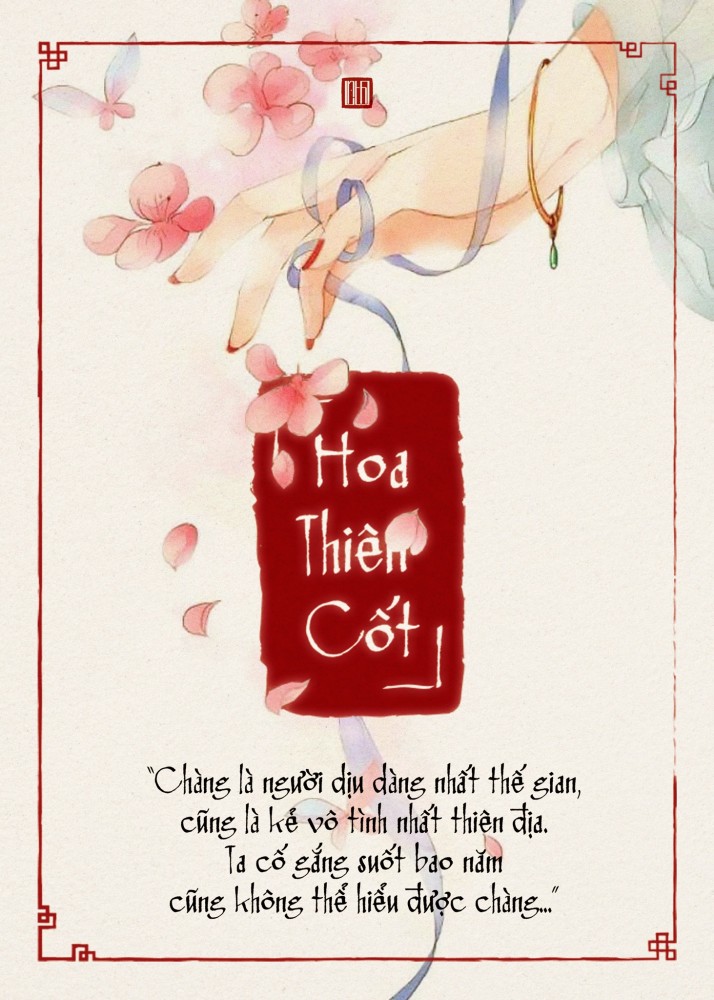
Khám phá sự độc đáo của Font việt hóa LNTH Dieter Steffmann trong thiết kế
Trong thế giới thiết kế đồ họa, việc lựa chọn Font Chữ phù hợp đóng vai trò then chốt trong việc truyền tải thông điệp và tạo ấn tượng thị giác. Gần đây, cộng đồng thiết kế Việt Nam đang dành sự quan tâm đặc biệt cho một tác phẩm nghệ thuật chữ cái: Font việt hóa LNTH Dieter Steffmann. Đây không chỉ là một bộ font thông thường, mà còn là sự kết hợp tinh tế giữa nét cổ điển Châu Âu và khả năng ứng dụng linh hoạt trong ngôn ngữ Tiếng Việt. Bộ font này, vốn được phục chế từ các mẫu chữ lịch sử bởi Dieter Steffmann, đã được nhóm LNTH việt hóa một cách tỉ mỉ, mở ra cánh cửa sáng tạo mới cho các dự án đòi hỏi sự trang trọng, cổ kính và độc đáo. Chúng ta sẽ cùng đi sâu tìm hiểu về lịch sử, đặc điểm và cách tối ưu hóa việc sử dụng bộ font tuyệt vời này.
Font việt hóa LNTH Dieter Steffmann: Khi cổ điển gặp hiện đại
Bộ font này là một ví dụ điển hình về sự giao thoa giữa nghệ thuật phục chế font chữ và công nghệ việt hóa hiện đại. Dieter Steffmann, một nhà phục chế font nổi tiếng người Đức, đã dành nhiều năm để số hóa và tái tạo lại hàng trăm mẫu chữ cổ điển từ các bản in lịch sử. Các tác phẩm của ông thường mang đậm phong cách Calligraphy (thư pháp) hoặc Blackletter (chữ Gothic), tạo nên vẻ đẹp trang nghiêm, hoài cổ mà hiếm có phông chữ hiện đại nào có thể sánh được. Khi bộ font gốc được nhóm LNTH (có thể là một nhóm Việt hóa font uy tín) tiếp nhận, thách thức lớn nhất là làm thế nào để giữ nguyên tinh thần cổ điển đó đồng thời bổ sung đầy đủ các ký tự tiếng Việt (dấu thanh, chữ cái có dấu mũ, v.v.).
Dieter Steffmann và di sản phục chế font
Dieter Steffmann không chỉ là người số hóa; ông là người bảo tồn di sản chữ viết. Công việc của ông giúp cho các nhà thiết kế ngày nay có thể tiếp cận những kiểu chữ đã từng thịnh hành từ thế kỷ 18, 19. Các font chữ của ông thường được chia sẻ miễn phí cho mục đích cá nhân, điều này đã giúp các tác phẩm như Font việt hóa LNTH Dieter Steffmann trở nên phổ biến nhanh chóng. Chất lượng phục chế cao, đường nét sắc sảo, và cấu trúc chữ cân đối là những yếu tố khiến các font của Steffmann được giới chuyên môn đánh giá rất cao. Điều này đặt nền móng vững chắc cho quá trình việt hóa sau này.
Đặc điểm nổi bật của phông chữ LNTH đã được việt hóa
Quá trình việt hóa đòi hỏi sự tinh tế và am hiểu sâu sắc về typography tiếng Việt. Nhóm LNTH đã phải tính toán kỹ lưỡng để các dấu thanh (sắc, huyền, hỏi, ngã, nặng) không làm mất đi sự hài hòa của nét chữ cổ điển. Kết quả là một bộ font hoàn chỉnh, hỗ trợ tối đa cho việc trình bày văn bản tiếng Việt mà vẫn giữ được đặc trưng của phong cách Dieter Steffmann. Các điểm mạnh bao gồm: độ rõ nét cao ngay cả ở kích thước nhỏ, phong cách trang trọng phù hợp cho tiêu đề và nội dung chính, và đặc biệt là sự tương thích tốt với các phần mềm thiết kế phổ biến như Adobe Photoshop, Illustrator hay các ứng dụng văn phòng. Đây là lựa chọn lý tưởng cho các ấn phẩm kỷ yếu, giấy khen, bằng tốt nghiệp (rất quan trọng cho học sinh, sinh viên và các kỳ thi tốt nghiệp), hay các dự án mang tính lịch sử.
Ứng dụng thực tế của font LNTH Dieter Steffmann trong thiết kế
Sự trang trọng và tính thẩm mỹ cao của font này mở ra vô số ứng dụng trong thiết kế đồ họa. Đối với các cơ sở giáo dục, việc sử dụng Font việt hóa LNTH Dieter Steffmann trong việc thiết kế bằng khen, chứng chỉ hoặc thư mời tham dự lễ tốt nghiệp sẽ tăng thêm giá trị lịch sử và sự trang nghiêm cho tài liệu. Đây là một yếu tố nhỏ nhưng tạo nên sự khác biệt lớn trong nhận thức về chất lượng và sự chuyên nghiệp.
Sử dụng trong ấn phẩm trang trọng và bằng cấp
Hãy tưởng tượng một tấm bằng tốt nghiệp trung học phổ thông hoặc đại học được in bằng một phông chữ có đường nét cổ điển, tinh xảo. Font chữ này mang lại cảm giác về di sản và truyền thống học thuật. Nó không chỉ là chữ viết; nó là biểu tượng của sự thành tựu. Ngoài ra, trong các dự án phục dựng tài liệu cổ, hay thiết kế sách giáo khoa lịch sử, việc sử dụng font này giúp tạo ra một không khí chân thực và đáng tin cậy. Các nhà thiết kế chuyên nghiệp thường tìm kiếm những font chữ có khả năng gợi lên cảm xúc, và font của Steffmann là một ứng cử viên sáng giá cho những mục đích này.
Tạo dấu ấn cho thương hiệu và bao bì
Không chỉ giới hạn trong lĩnh vực giáo dục hay tài liệu trang trọng, Font việt hóa LNTH Dieter Steffmann còn được các nhà thiết kế thương hiệu yêu thích khi muốn xây dựng hình ảnh cổ điển, sang trọng cho sản phẩm. Ví dụ, nó rất phù hợp cho các nhãn hiệu rượu vang, cà phê cao cấp, hoặc các sản phẩm thủ công mỹ nghệ. Sự pha trộn giữa nét Blackletter và sự mềm mại của dấu tiếng Việt tạo nên một vẻ ngoài độc đáo, khó quên. Điều quan trọng khi sử dụng là phải cân bằng với các yếu tố thiết kế khác để tránh làm cho tổng thể bị quá nặng nề hoặc khó đọc. Phối hợp nó với một font sans-serif hiện đại cho phần thân văn bản nhỏ hơn là một chiến lược SEO hiệu quả trong thiết kế đồ họa, giúp thu hút người dùng tìm kiếm sự kết hợp giữa truyền thống và hiện đại.
Tóm lại, Font việt hóa LNTH Dieter Steffmann là một tài nguyên quý giá trong kho tàng typography Việt Nam. Nó minh chứng cho sự cống hiến của các nhà phục chế và việt hóa trong việc mang lại những tinh hoa chữ viết quốc tế cho cộng đồng sáng tạo trong nước. Dù bạn là một học sinh đang chuẩn bị cho các ấn phẩm cuối khóa, một sinh viên thiết kế đồ họa, hay một chuyên gia SEO đang tìm kiếm sự khác biệt cho website, bộ Font Chữ này chắc chắn sẽ là một công cụ mạnh mẽ. Việc tích hợp các yếu tố cổ điển như bộ font này vào các dự án sẽ giúp tác phẩm của bạn nổi bật, truyền tải được sự trang trọng và chiều sâu lịch sử. Hãy khám phá và ứng dụng ngay hôm nay để thấy được sự khác biệt mà chất lượng cao cấp này mang lại.